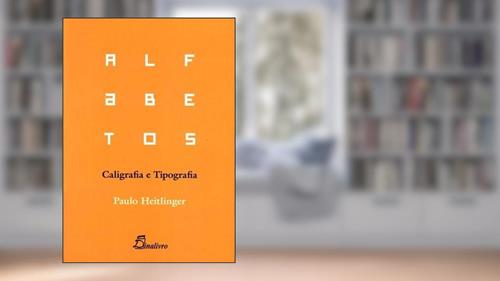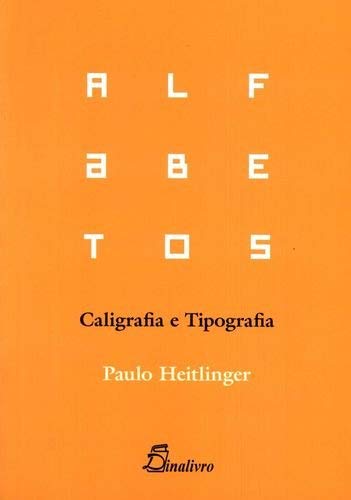
Resumo de Alfabetos. Caligrafia e Tipografia, de Paulo Heitlinger
Mergulhe na arte das letras com 'Alfabetos. Caligrafia e Tipografia' de Paulo Heitlinger. Descubra como a tipografia transforma a comunicação!
Alfabetos. Caligrafia e Tipografia, do autor Paulo Heitlinger
Prepare-se para entrar no fascinante mundo das letras com Alfabetos. Caligrafia e Tipografia, de Paulo Heitlinger. Se você já se perguntou por que a letra "A" é tão superior ao "Q" que parece ter saído de um filme de terror, este livro é a sua chance de descobrir!
Nesta obra, Heitlinger nos leva a uma jornada pela evolução das formas de escrita e tipografia, desde as rudimentares inscrições em pedras até os sofisticados tipos digitais que usamos hoje. E sim, eles têm suas próprias biografias - quem diria que uma simples letra poderia viver uma vida tão cheia de drama?
Vamos aos highlights do livro. O autor começa nos apresentando os diferentes alfabetos que surgiram ao longo da história. Você sabia que as letras que usamos hoje na verdade têm uma longa linha de parentesco com os hieróglifos egípcios? Pois é, a caligrafia e a tipografia têm mais conexões familiares do que você pode imaginar. É tipo um grande reality show das letras!
Em seguida, Heitlinger mergulha na caligrafia. Não é só sobre fazer gatinhos com a caneta, meus amigos! É uma arte que exige prática e, claro, um traço perfeito. Aprenda sobre as diferentes técnicas, as ferramentas e até a história de alguns calígrafos que levaram suas habilidades tão a sério que praticamente transformaram suas canetas em varinhas mágicas. Quase dá pra sentir o cheiro da tinta!
E, claro, não podemos esquecer da tipografia. Heitlinger faz uma análise detalhada das fontes, seus estilos e como elas influenciam nossa leitura e entendimento. O autor traz à tona a eterna batalha entre as fontes serifadas e sem serifa, uma rivalidade que nem a torcida de futebol mais fervorosa consegue superar. Quem diria que Arial e Times New Roman eram inimigas mortais?
Ah, e a parte de tipografia digital? É um verdadeiro festival! O autor explica como as novas tecnologias mudaram a forma como criamos e consumimos texto. Hoje, podemos ter uma fonte que brilha no escuro, enquanto nossos antepassados se contentavam em apagar a poeira dos pergaminhos. Olha a evolução, galera!
E não se preocupe, não há spoilers aqui porque, vamos ser honestos, ninguém está realmente ansioso para saber qual será o próximo estilo de fonte. Mas a visão de Heitlinger sobre como a caligrafia e a tipografia estão conectadas ao nosso cotidiano é inspiradora e, sim, pode até fazer você olhar para aquela letra rabiscada ao lado do seu caderno com um novo respeito.
Assim, Alfabetos. Caligrafia e Tipografia não é só um guia para aprender mais sobre letras; é uma ode à beleza e complexidade da comunicação escrita. Se você sempre achou que a tipografia era apenas um detalhe, é hora de rever seus conceitos. Agora, vá lá e transforme suas mensagens de texto - porque uma boa tipografia faz toda a diferença, mesmo no WhatsApp!